Tirar a serifa dos logotipos para deixar com um ar de algo mais novo e próprio para os ambientes digitais, tornou-se uma tendência no mercado. Recentemente escrevemos um artigo sobre o Santander, que também renovou sua identidade visual deixando a serifa de lado.
O HSBC, um dos maiores bancos do mundo, também passou por uma reformulação parecida. O redesign teve como principal objetivo alinhar a marca com sua principal missão que é de ajudar as pessoas a prosperarem.
O novo logotipo não sofreu muitas alterações e ainda apresenta a identidade do banco, com seu icônico hexágono vermelho e branco. O novo logotipo, no entanto, possui uma fonte sans serif e um vermelho mais profundo.
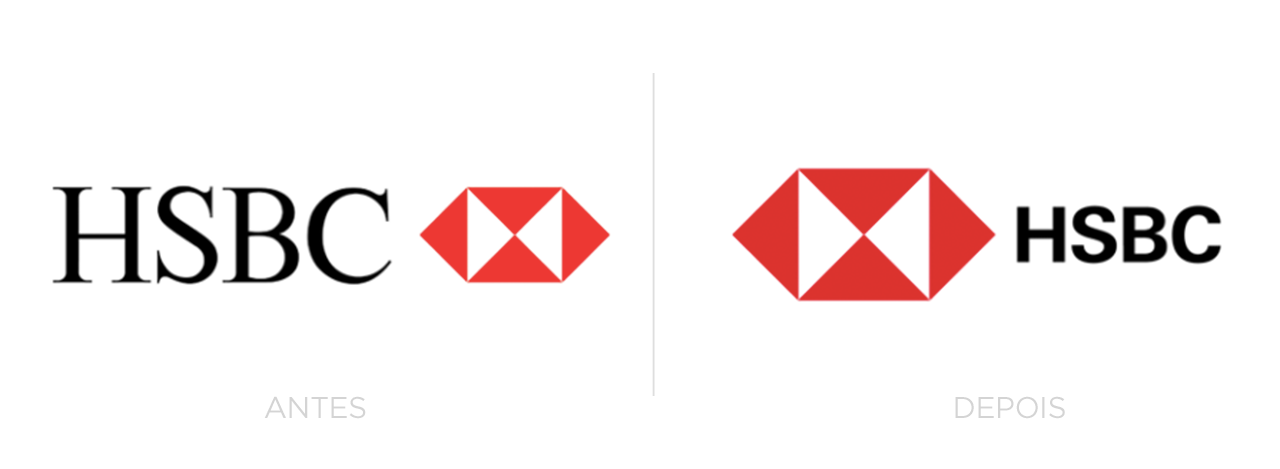
O símbolo também está maior em comparação com o logotipo antigo e redimensionado propositalmente para ter um encaixe menos alinhado com as letras HSBC.
Para acompanhar a transformação, o banco lançou uma campanha chamada “Juntos prosperamos“, com novas peças publicitárias em seus anúncios, para refletir sua mensagem de estar comprometido em ajudar seus clientes com suas metas.